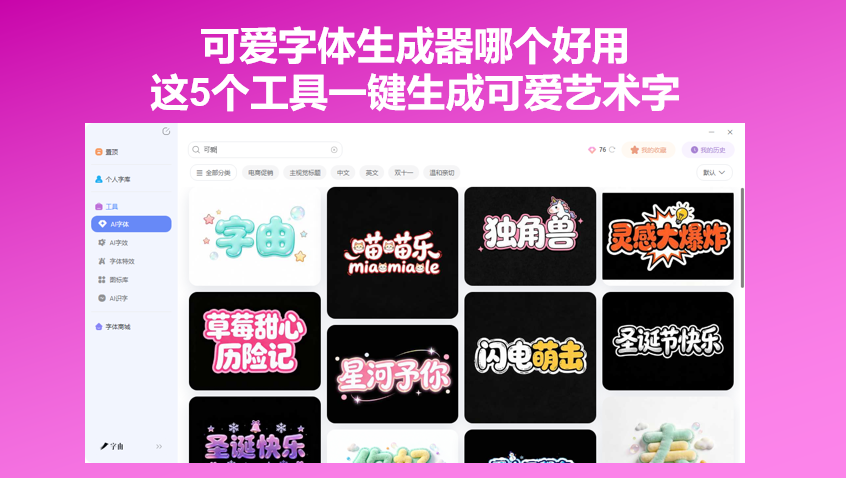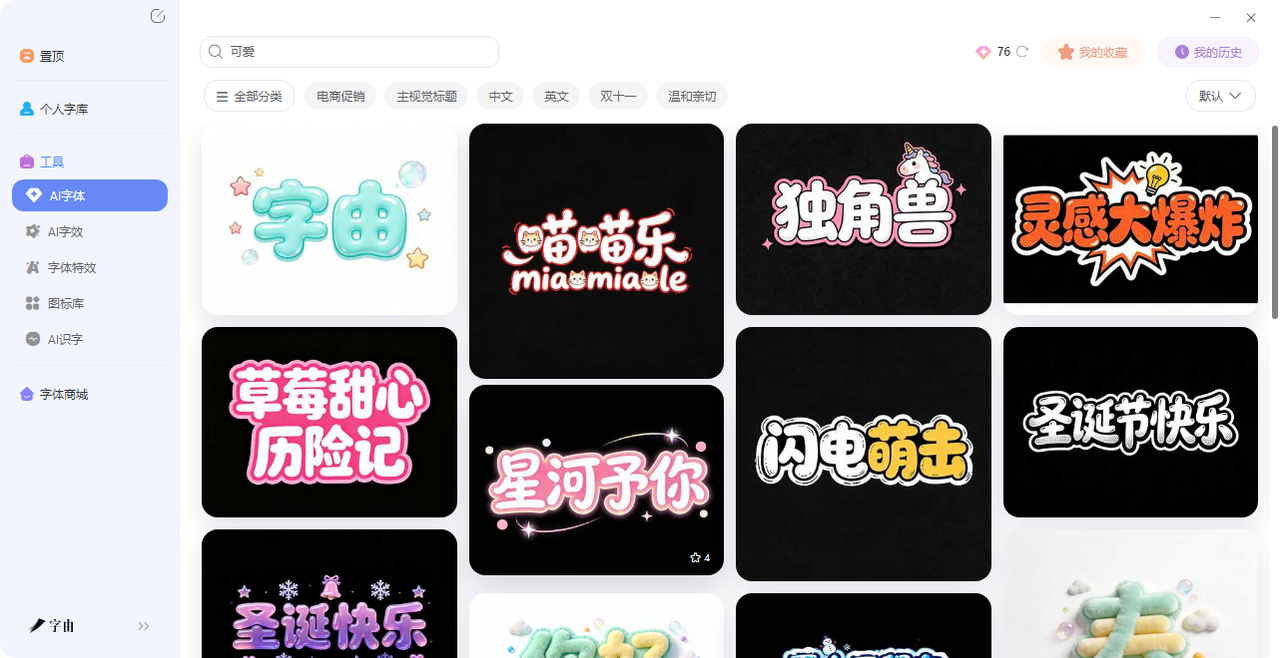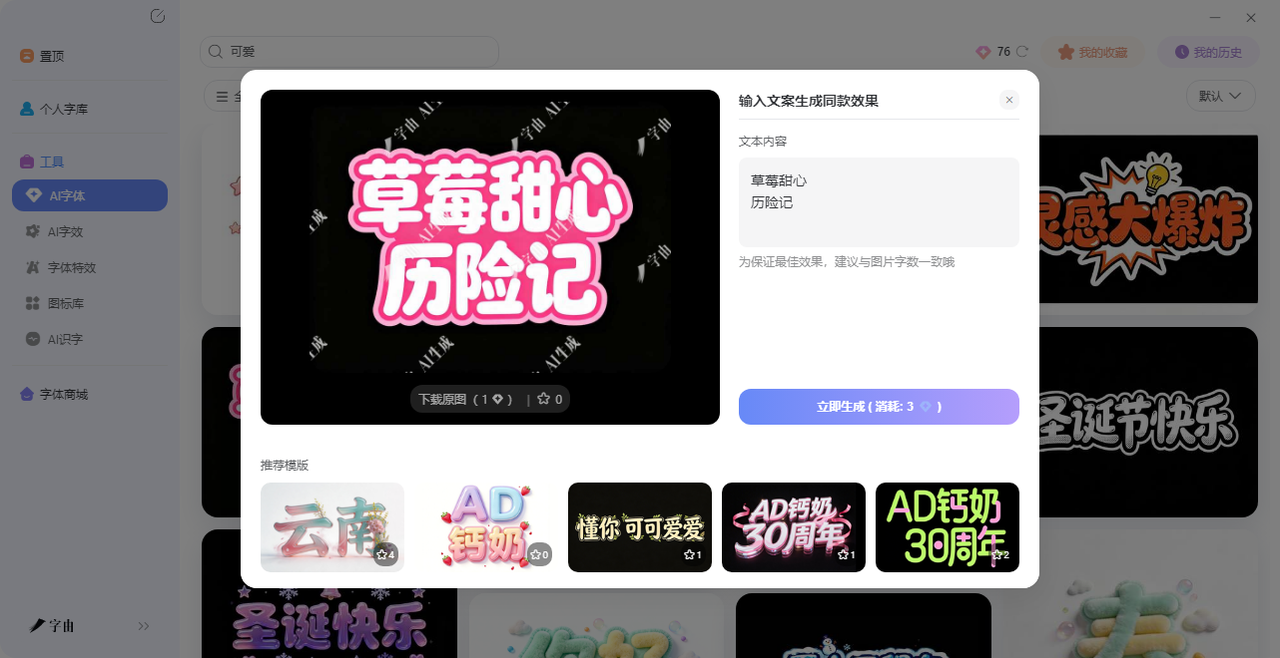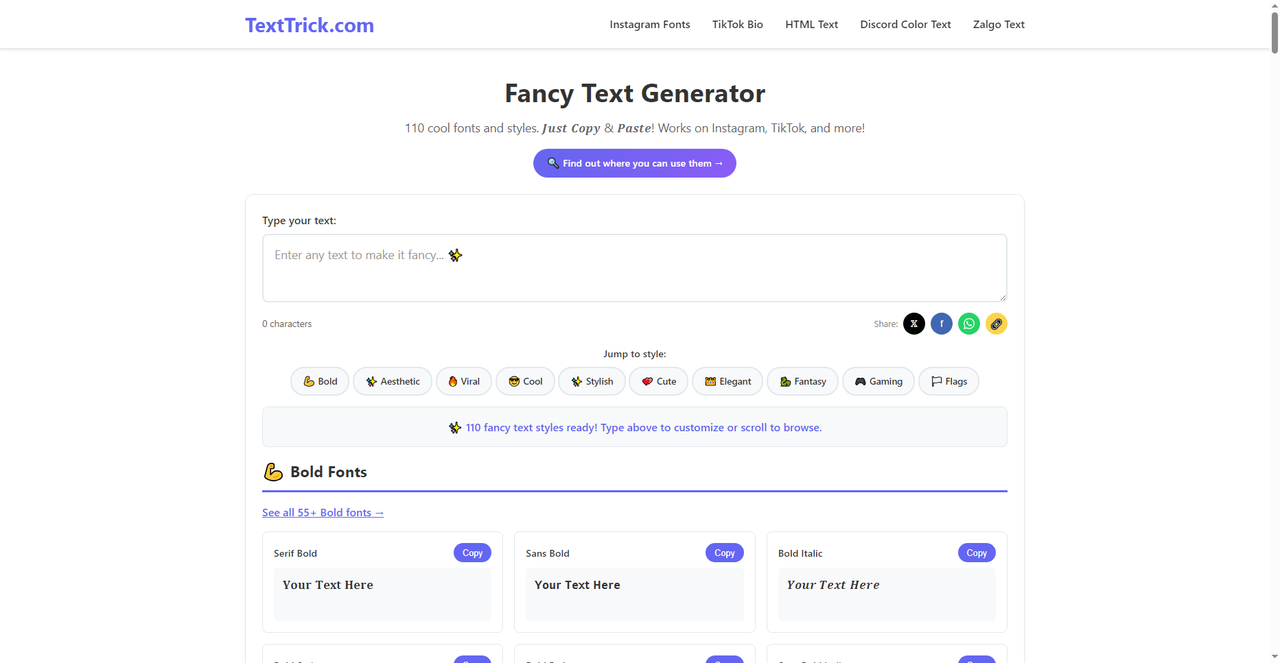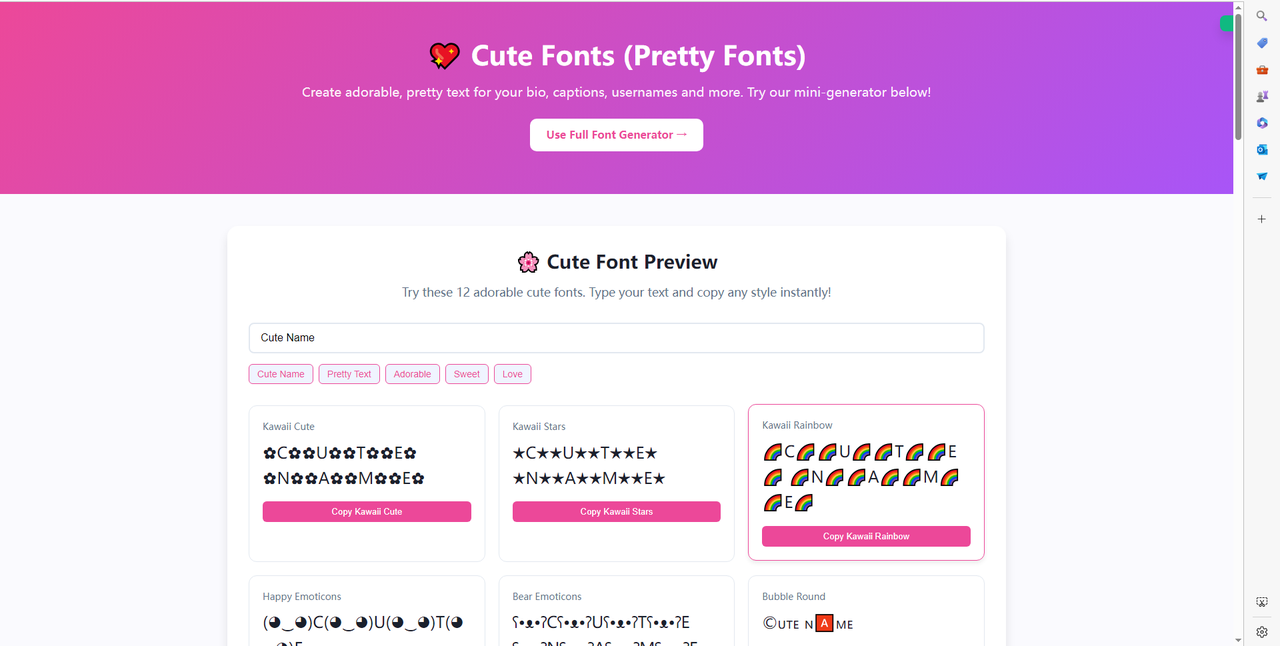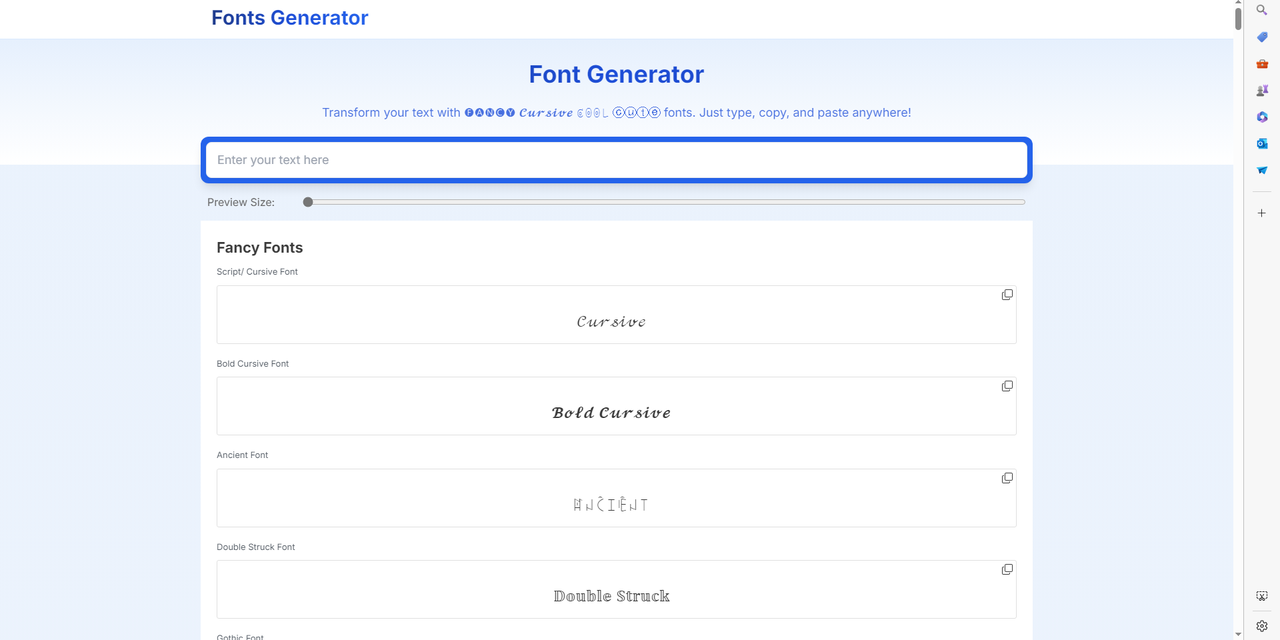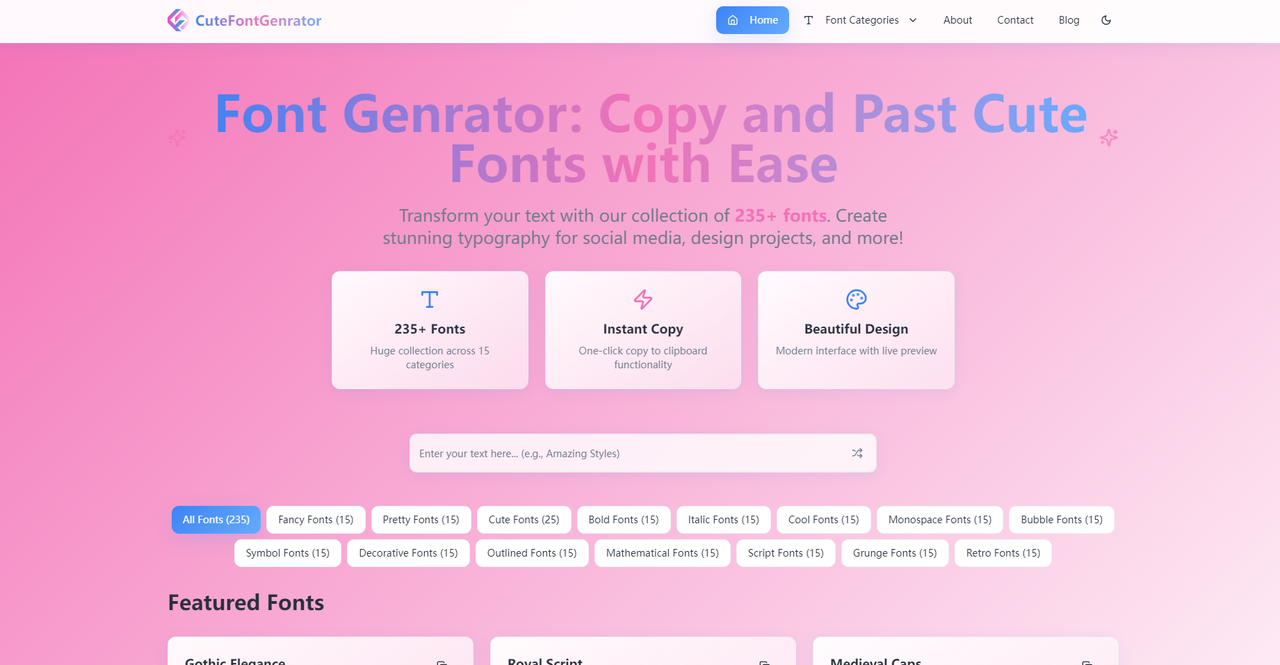
可爱字体生成器哪个好用?这5个工具一键生成可爱艺术字
当我们设计关于小动物或者是可爱的东西的周边的时候,肯定就不能再用一般的字体了,不论是等线字体还是无衬线字体,都稍显死板,但是想要那种圆圆的、软软的、带点小装饰的 可爱字体,但自己不会设计,手写又不太美观怎么办?没关系,可爱字体生成器可以帮你解决这个问题,输入文字,选个风格,一键生成,复制粘贴就能用。今天我整理了 5 个工具,非常适合生成可爱风格的艺术字,快来一起看看吧!
第一个要介绍的网站是字由,字由是一个集字体库、字体管理、AI 工具于一体的客户端,目前收录超过 10500 款字体,其中 3585 款免费商用。打开客户端,你会发现可爱风格的字体非常多。但是今天我们就要重点介绍的是字由的AI字体功能,如果你想找一个真正好用的 可爱字体生成器,字由的 AI 字体功能值得一试。它不像在线站那样只能生成 Unicode 字符,而是直接出图,画质清晰,没有水印,模板还一直在更新。
打开字由客户端,左侧导航栏找到“工具” → “AI 字体”。进去之后,你会看到各种风格的模板。你可以搜索“可爱”之类的关键词,就会展示可爱风格这一类的AI字体:
萌音乐:软萌风格,带音乐元素
miamisale:复古可爱,像甜品店招牌
独角兽:梦幻、少女心
灵感大爆炸:活泼卡通,带爆炸效果
草莓甜心:圆润粉嫩,甜味十足
历险记:儿童故事书风格
星河予你:浪漫闪亮,星空主题
闪电萌击:可爱中带点小酷
圣诞节快乐:节日氛围可爱字体
这些不是字体文件,而是模板。你点击任何一个模板,进入编辑界面,把默认文字改成你自己的文案,比如“生日快乐”“今天也要开心”,然后点击生成。字由的 AI 会把你输入的文字,按照该模板的风格渲染成一张艺术字图片。
除了这些预设模板,你还可以在 AI 字体功能里自己选风格——比如“可爱”“卡通”“圆润”等标签,字由会生成多种变体供你选择。
还需要提醒的是,如果你在用字由的 AI 字体生成可爱艺术字时,发现默认模板不够用,可以点一下“更多风格”或者切换“可爱”分类下的不同标签。字由的 AI 字体模板会不定期更新,节假日(比如圣诞、情人节)还会上线限时主题模板。生成图片时建议把画布尺寸选大一点(比如 1920×1080),这样拖进海报或者 PPT 里不会模糊。另外,生成后的图片背景默认是透明的,方便你直接叠加到其他设计素材上。
2、TextTrick
第二个要介绍的网站是TextTrick,一个功能很全的在线字体生成器。页面上方写着“110 cool fonts and styles. Just Copy & Paste! Works on Instagram, TikTok, and more!”输入框里可以打任何文字,右侧显示字符计数。下面有风格分类:Bold、Aesthetic、Viral、Cool、Stylish、Cute、Elegant、Fantasy、Gaming、Flags 等。点击 Cute 分类,会展示所有可爱风格的字体样式。每个样式旁边都有一个“Copy”按钮,点一下就能复制转换后的文字。
3、Cute Fonts
这个网站是一个专门做可爱字体的生成器,页面非常简洁。标题是“Cute Fonts (Pretty Fonts)”,副标题“Create adorable, pretty text for your bio, captions, usernames and more.”它提供了一个“Cute Font Preview”区域,展示了 12 种可爱的字体样式。每个样式下面都有一行示例文字,比如“Cute Name”“Pretty Text”“Adorable”“Sweet”“Love”。你可以在输入框里打自己的文字,然后所有样式会同步更新。
4、Fonts Generator
Fonts Generator 的页面相对简单。它主打 Cursive(草书)和 Curse(可能是 Cursive 的笔误)字体。下面列出了几个分类:
Script/Curse Font
Bold Curse Font
Ancient Font
Double Struck Font
Gothic Font
其中 Double Struck 是一种双线字体,看起来像字母的轮廓被加粗了一圈,很有卡通感,可以归类为可爱风格的一种。Gothic Font 虽然名字是哥特,但有些哥特字体也可以很可爱,比如圆润的
黑体变种。这个站的功能比较基础,输入文字后,下面会展示几种转换结果,每个结果旁边有复制按钮。适合偶尔用一下。
5、Font Generator
网站是功能最强的——Font Generator: Copy and Paste Cute Fonts with Ease。它声称有 235+ 种字体,分成 15 个类别,主要包括:
All Fonts (235)
Fancy Fonts (15)
Pretty Fonts (15)
Cute Fonts (25)
Bold Fonts (15)
Italic Fonts (15)
光 Cute Fonts 一个分类就有 25 种样式,比其他几个站加起来还多。页面顶部有输入框,输入文字后,下面会展示所有样式的预览。每个样式都可以一键复制。这个站还有一个特色:每个分类旁边标注了字体数量,你可以直接点击分类,只显示那一类的字体,不用在所有样式中翻找。这个网站适合需要大量可爱字体选择的人。25 种可爱风格,基本能满足日常社交媒体和创意文字的需求。